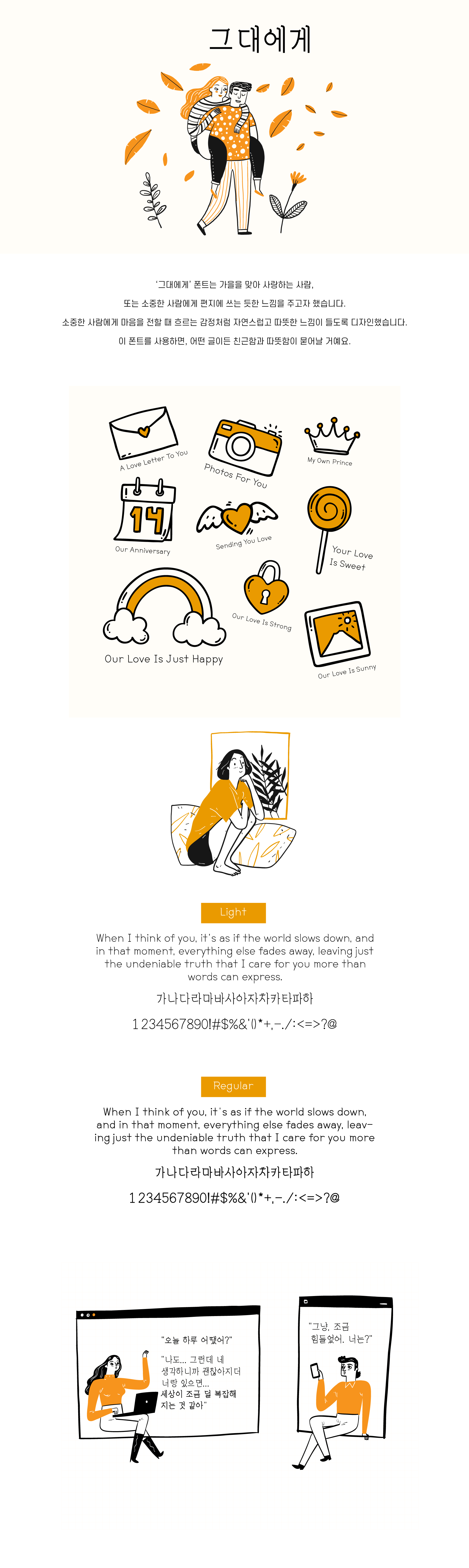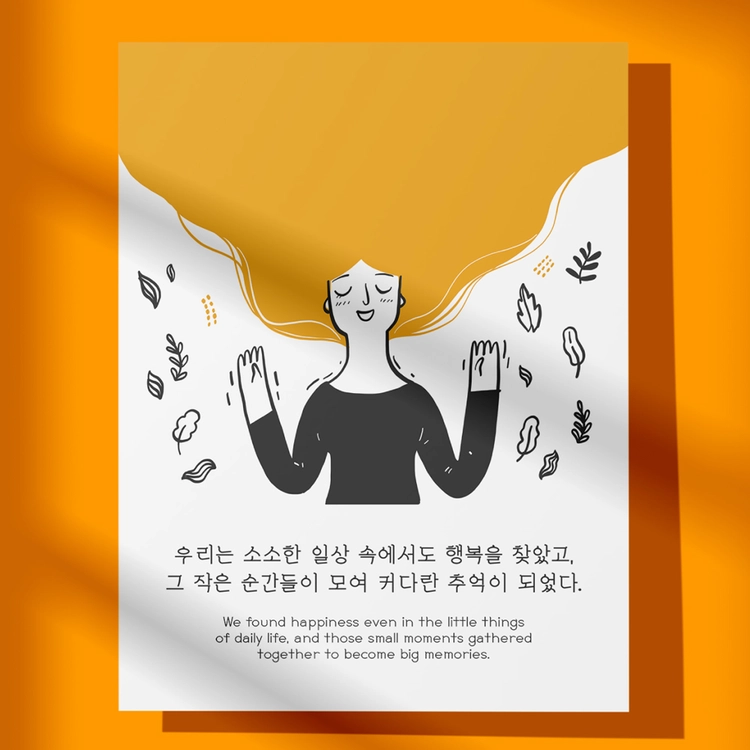
그대에게'폰트는 가을을 맞아 사랑하는 사람, 또는 소중한 사람에게 편지에 쓰는 듯한 느낌을 주고자 했습니다. 소중한 사람에게 마음을 전할 때 흐르는 감정처럼 자연스럽고 따뜻한 느낌이 들도록 디자인했습니다. 이 폰트를 사용하면, 어떤 글이든 친근함과 따뜻함이 묻어날 거예요.